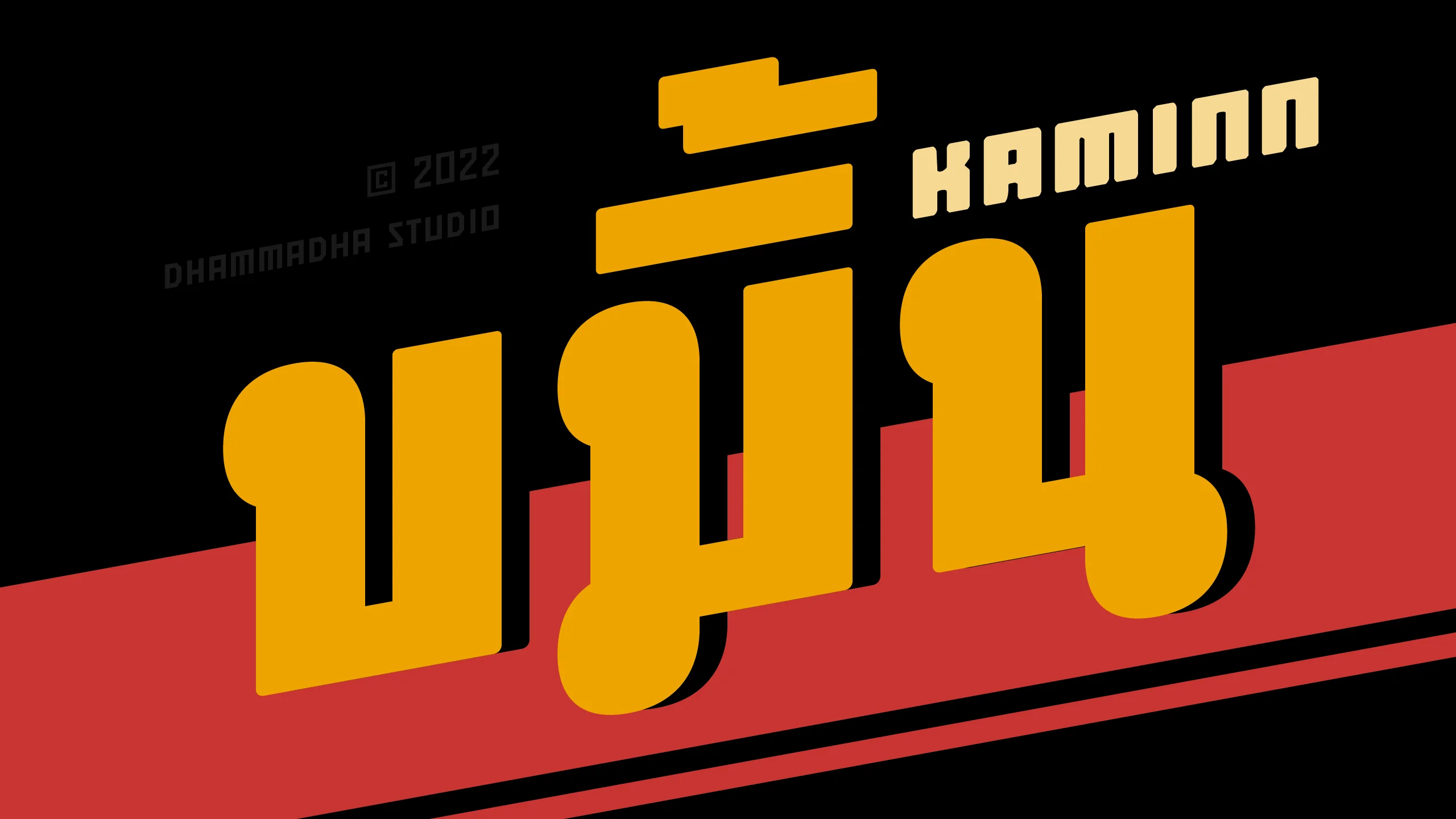
ชุดอักษรพาดหัวที่สะท้อนถึงความสง่างามและความ "เก๋า" ของงานออกแบบไทยร่วมสมัย โดยได้รับแรงบันดาลใจอันเปี่ยมล้นมาจากลายเส้นบน ปกแผ่นเสียง (LP) "แม่นางนกขมิ้น" ของคุณสมยศ ทัศนพันธ์ ศิลปินระดับตำนานผู้ครอบครองรางวัลแผ่นเสียงทองคำพระราชทาน เราได้หยิบนำความประณีตของศิลปะยุควันวานมาขัดเกลาใหม่ให้ดูโดดเด่นและมีพลัง สร้างสมดุลระหว่างความคลาสสิกที่ชวนให้หวนคิดถึงกับความร่วมสมัยที่จัดวางได้อย่างลงตัวในงานดีไซน์ยุคปัจจุบัน ด้วยบุคลิกที่ดูเข้มข้นและมีเรื่องราวในตัวเอง "ขมิ้น | KAMINN" จึงออกแบบมาเพื่อเป็นฟอนต์ Display สำหรับงานพาดหัวที่ต้องการความเก๋า ความเท่ และโดดเด่นสะดุดตา มอบบรรยากาศที่เปี่ยมด้วยรสนิยมสไตล์ไทยวินเทจที่ไม่เหมือนใคร เหมาะอย่างยิ่งสำหรับงานสร้างอัตลักษณ์แบรนด์ งานออกแบบสื่อสิ่งพิมพ์ที่เน้นอารมณ์ศิลป์ หรือการจัดวางกราฟิกที่ต้องการส่งต่อคุณค่าทางวัฒนธรรมผ่านตัวอักษรที่ทรงเสน่ห์และมีเอกลักษณ์ระดับครู พิเศษ !! ชุดฟอนต์ KAMINN ERODED ทำมาเก่าเป็นพิเศษ พร้อมให้ใช้งานได้ทันที แถมฟรี !! เมื่อสั่งซื้อ KAMINN FULL FAMILY